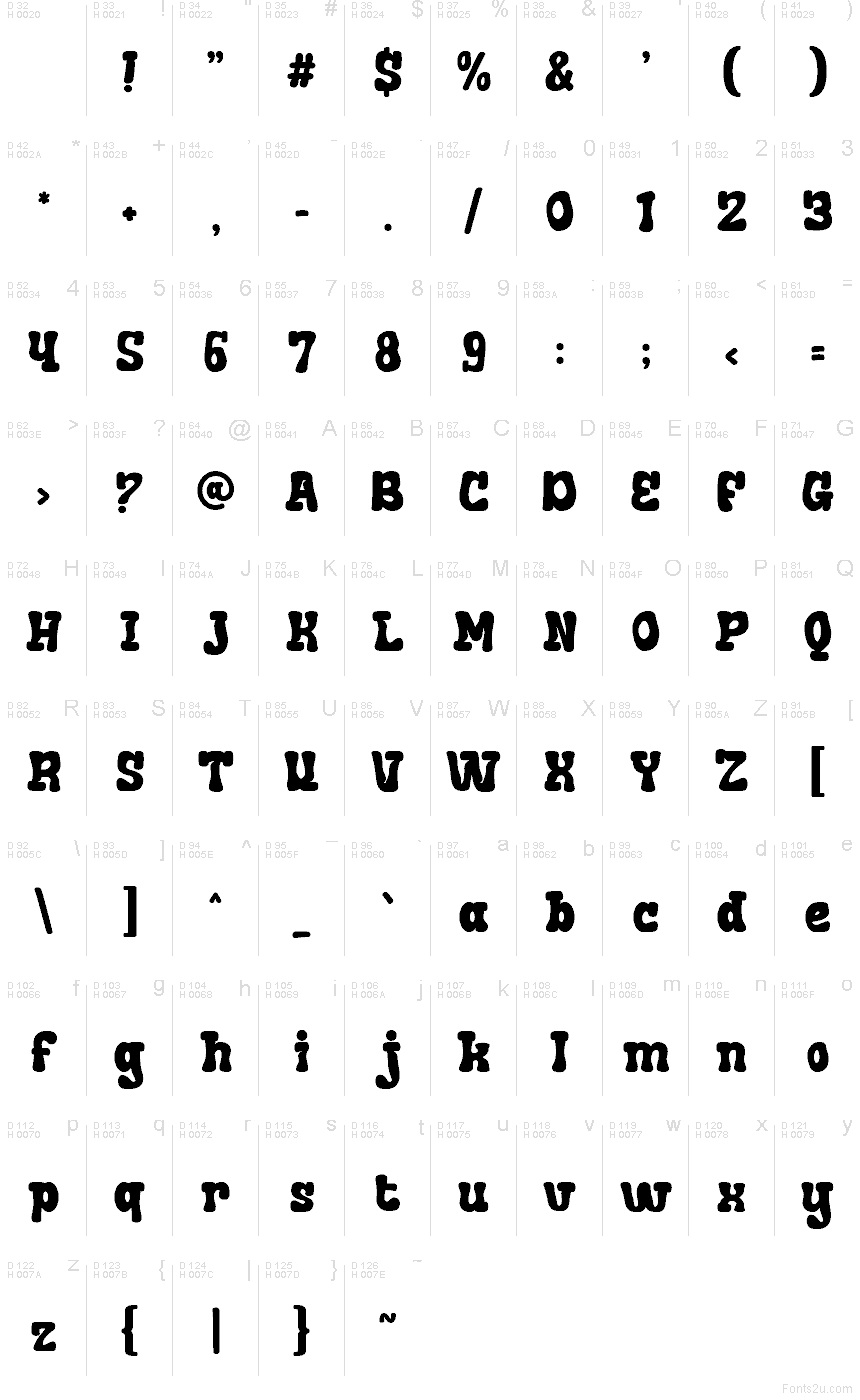
Faded Glory Display od Putracetol Studio je groovy font, jehož tvary vycházejí z měkkých, zaoblených siluet. Působí jemně a mírně roztekle, nikoliv ostře řezaně. Tento hravý rytmus dodává písmu uvolněnou atmosféru plakátů ze 70. let, se širokými křivkami a plnými vnitřními prostory, díky nimž tvary působí živě a ne strnule.
Nejlépe se vyjímá na obalech alb, brandingu kaváren, retro letácích, obalech produktů nebo krátkých grafikách na sociální sítě, kde může vyniknout jeho buclatý charakter. Díky tomu, jak se tvary přirozeně rozšiřují, dodává Faded Glory Display velkým nadpisům a titulkům v logotypovém stylu vřelý a pohodový vzhled.